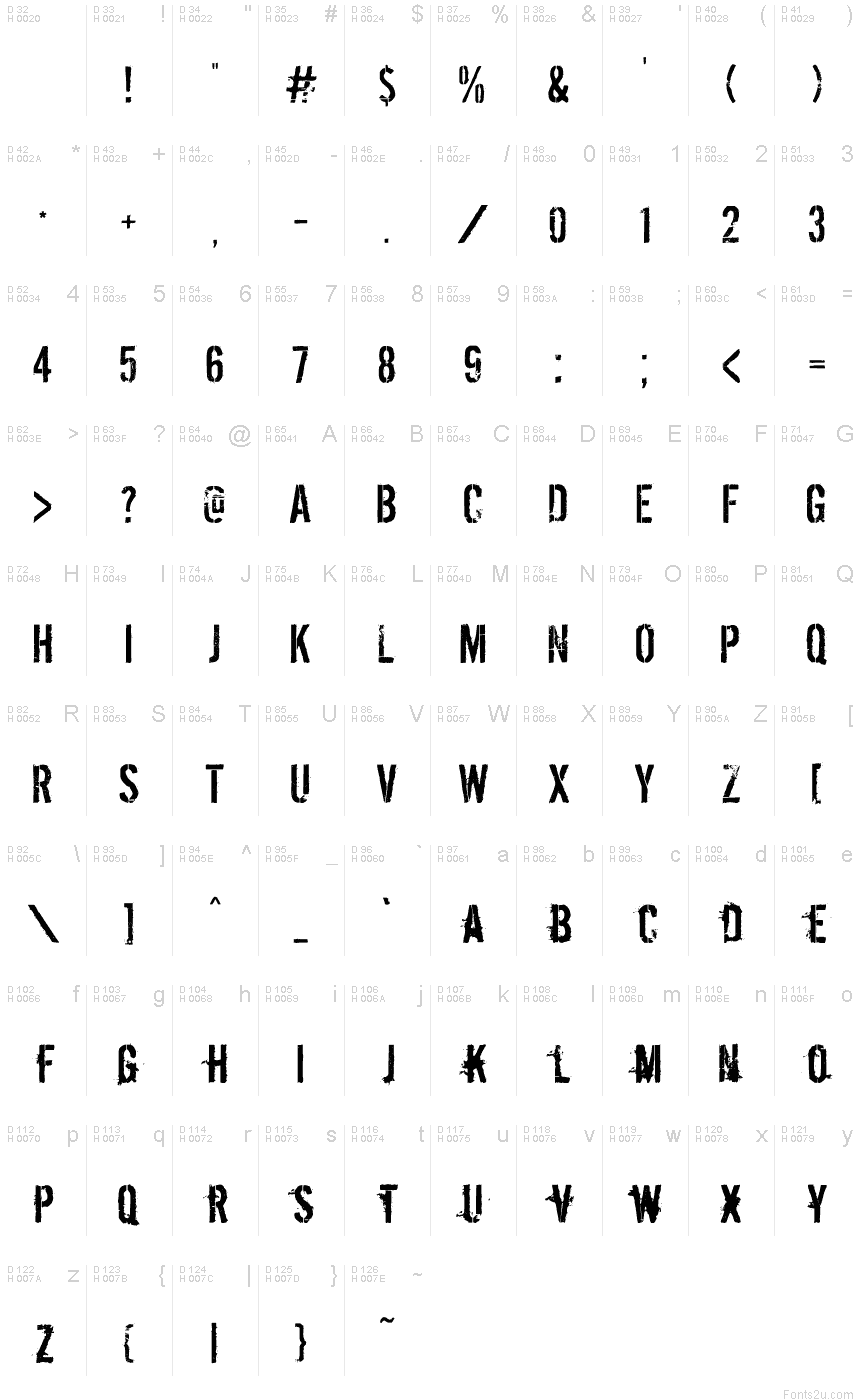
Dirty Ego
Dirty Ego od Eduardo Recife to darmowy, zniekształcony krój displayowy, wyglądający jak tusz przeciągnięty przez uszkodzone sito. Jego wysokie, skompresowane kształty oraz poszarpana, zachlapana faktura nadają każdemu słowu nerwowy, brudny puls, sprawiając, że nawet krótki nagłówek staje się głośny, surowy i odrobinę niebezpieczny.
Dirty Ego świetnie sprawdza się na plakatach koncertowych, grafikach skejtowych, okładkach zinów, oprawach płyt, tagach streetwearowych, horrorach i surowych materiałach do social mediów. Używaj go w dużym rozmiarze, aby zachować wyrazistość detali, a gdy potrzebujesz, by chaos był czytelny, zestaw ten darmowy font z prostym bezszeryfowcem, takim jak Helvetica lub Inter.